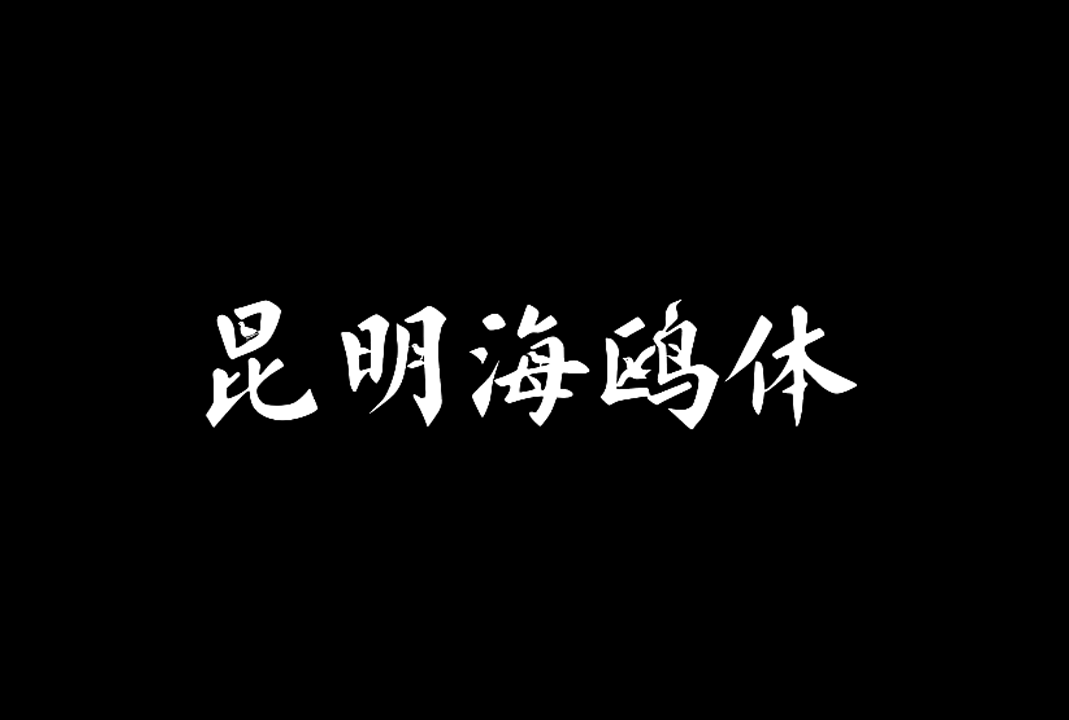
“昆明海鸥体”是由字体家AI神笔造字负责人、中国当代著名书法家叶根友为昆明送上专属的新年文化礼物。
“昆明海鸥体”字体,将海鸥元素融入书法中,既展现了书法的神韵之美,又彰显了昆明的观鸥风情,为昆明观鸥季赋予了独特的文化内涵,全套共6763个字,可满足大部分使用场景。
“昆明海鸥体”中的“昆明”两字中的都有红嘴鸥的形象,特别是“昆”字中的红嘴鸥形象,设计团队先后做了10多种造型,最后才选定一只站立红嘴鸥的形象。除了昆明两字中有海鸥形象之外,“滇池”“春城”“翠湖”“平安”“美满”等汉字的笔画中都有红嘴鸥的各种姿态。